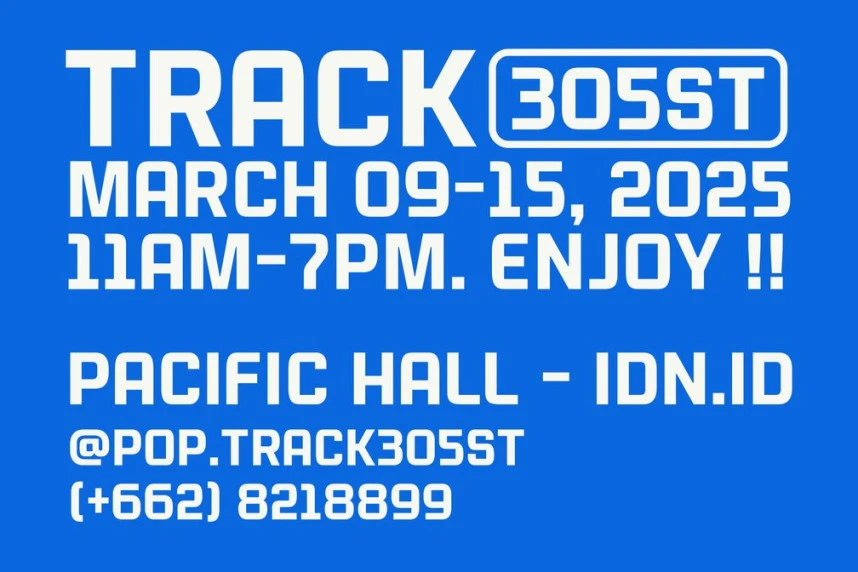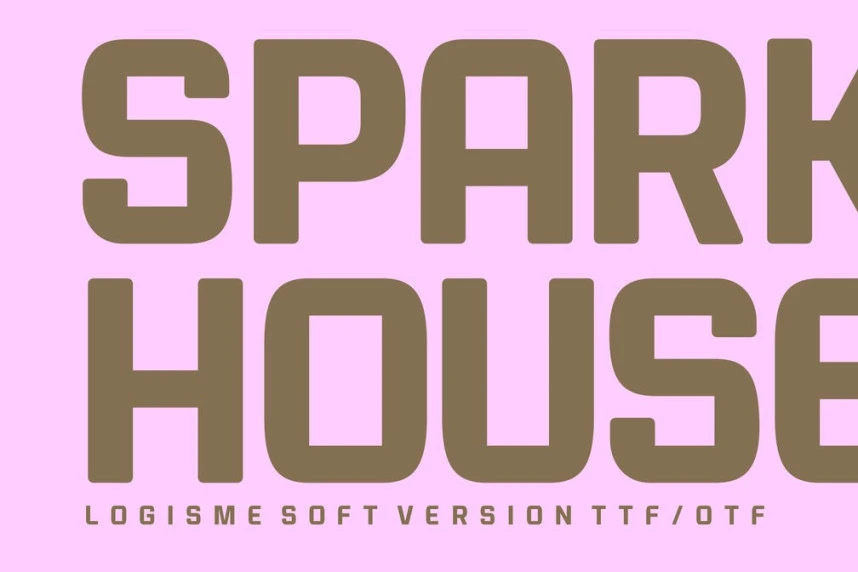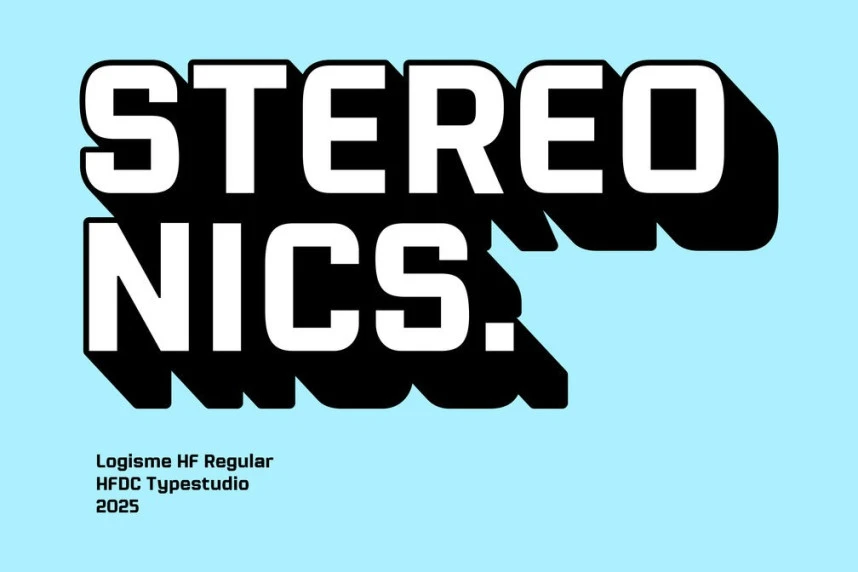
Logisme Futuristic Font
Logisme Futuristic Font, keskin geometrileri dinamik bir canlılıkla birleştiren şık ve gelecekçi bir gösteri yazı tipidir. Cesur bir ifade yaratmak üzere tasarlanmıştır; Logisme, başlıklar, afişler, marka çalışmaları ve keskin bir estetik talep eden her proje için mükemmeldir.
Logisme Futuristic Font, keskin geometriyi dinamik bir çekicilikle birleştiren şık ve geleceğe dönük bir gösteri yazı tipidir. Cesur bir ifade yaratmak üzere tasarlanmıştır; Logisme başlıklar, posterler, marka tasarımı ve keskin bir estetik talep eden herhangi bir proje için mükemmeldir.